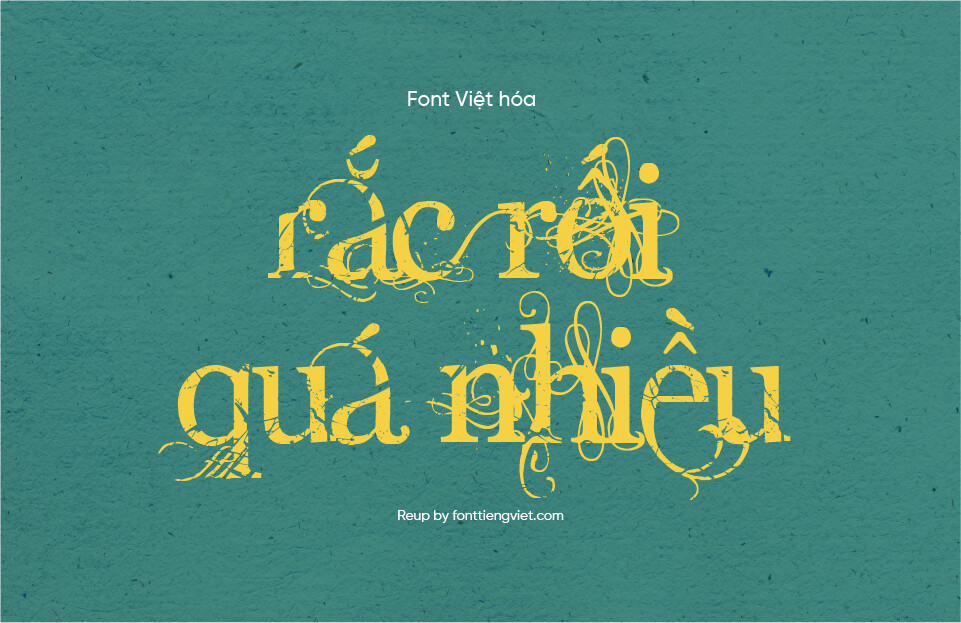
Font việt hóa UVF Angelic War
Giới thiệu bộ Font việt hóa UVF Angelic War
Trong thế giới đồ họa, việc tìm kiếm một Font Miễn Phí mang phong cách cổ điển nhưng vẫn giữ được nét hiện đại là điều không hề dễ dàng. Font việt hóa UVF Angelic War chính là sự lựa chọn hoàn hảo cho những ai yêu thích sự phá cách và tinh tế. Được chuyển ngữ sang tiếng Việt đầy đủ, bộ font này giúp người dùng dễ dàng ứng dụng vào các phần mềm thiết kế phổ biến mà không lo lỗi hiển thị dấu câu.
Đặc điểm thiết kế nổi bật
Bộ font này gây ấn tượng mạnh nhờ những đường nét thanh mảnh kết hợp với các chi tiết uốn lượn sắc sảo. Nó mang đến cảm giác vừa huyền bí, vừa mạnh mẽ, phù hợp cho nhiều loại dự án khác nhau. Với sự linh hoạt cao, người dùng có thể tạo ra những sản phẩm thị giác độc đáo, mang đậm dấu ấn cá nhân mà vẫn đảm bảo tính thẩm mỹ chuyên nghiệp.
Ứng dụng thực tế của Font việt hóa UVF Angelic War
Sử dụng trong giáo dục và sáng tạo
Đối với học sinh và sinh viên, Font việt hóa UVF Angelic War là công cụ tuyệt vời để trang trí bìa tiểu luận, làm thiệp chúc mừng hoặc thiết kế poster sự kiện trường học. Font chữ này giúp các thông điệp trở nên sinh động và thu hút sự chú ý hơn. Nhà trường cũng có thể sử dụng font này để thiết kế các bảng tin nghệ thuật nhằm khơi gợi cảm hứng học tập cho học sinh.
Lưu ý khi sử dụng trong đồ họa
Dù có thiết kế bắt mắt, bạn nên sử dụng font này cho các tiêu đề lớn hoặc câu trích dẫn ngắn để đạt hiệu quả thị giác tốt nhất. Việc kết hợp với các font chữ không chân tối giản sẽ giúp tổng thể thiết kế trở nên cân bằng và dễ đọc hơn đối với người xem.
Kết luận về bộ font nghệ thuật này